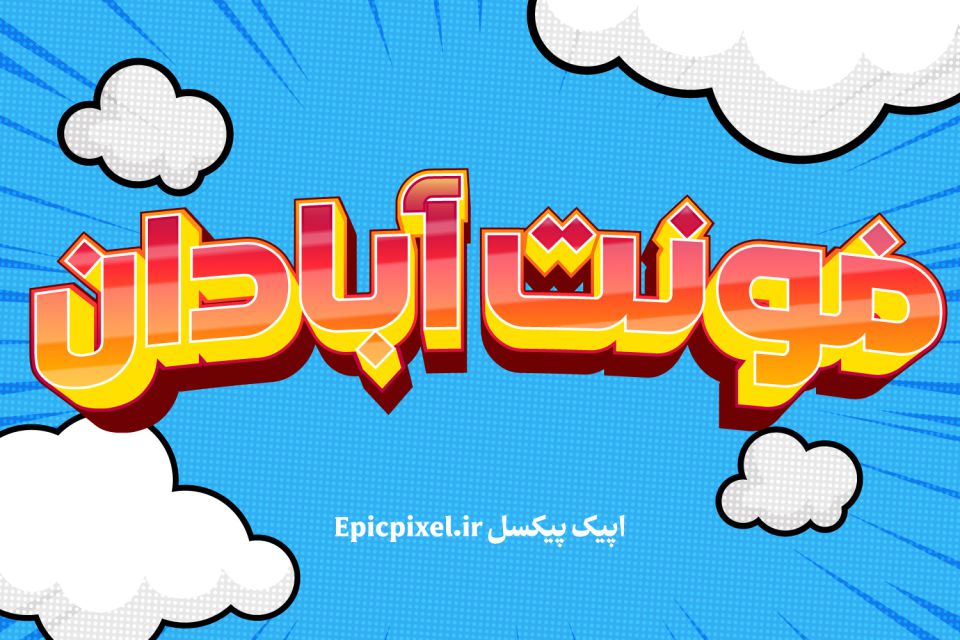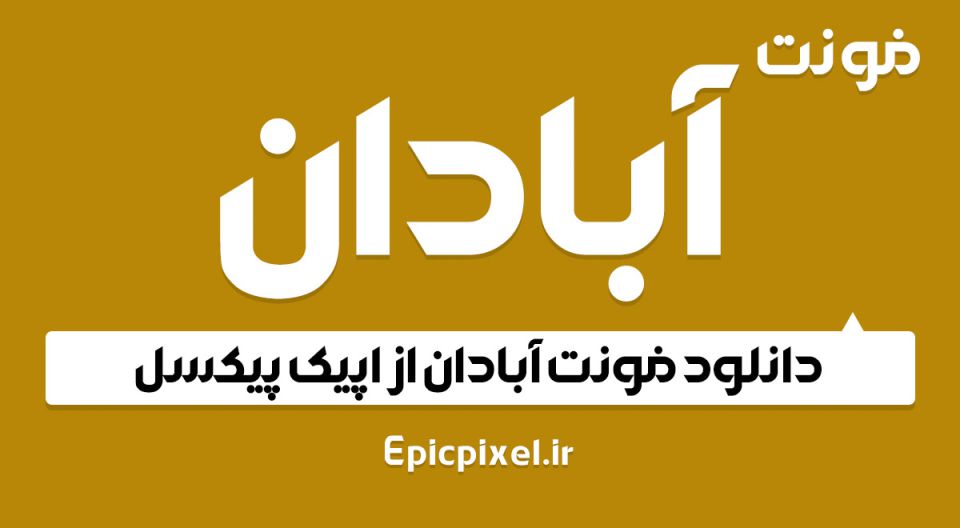
4 فونت آبادان فارسی
دانلود مجموعه کامل فونت Abadan فارسی Font اپیک آبادان |
| ⭐ توضیحات | دانلود فونت آبادان با ظاهری قدرتمند و خوانا، انتخابی ایدهآل برای طراحان گرافیک و علاقهمندان به تایپوگرافی است. این فونت برای طراحی لوگو، پوستر، وبسایت و… مناسب است.
دانلود فونت آبادان ارتقاء پروژههای گرافیکی با ظاهری قدرتمند
فونت آبادان، یک انتخاب برجسته برای طراحان گرافیک و علاقهمندان به تایپوگرافی است. این فونت با الهام از استحکام و پایداری شهر آبادان، ظاهری خوانا، حرفهای و در عین حال مدرن را به ارمغان میآورد. در این مقاله جامع، به بررسی کامل دانلود فونت آبادان، ویژگیهای برجسته آن، کاربردهای متنوع و نحوهی نصب آن میپردازیم.
چرا فونت آبادان را انتخاب کنیم؟
- خوانایی و وضوح بالا: فونت آبادان با طراحی دقیق و فاصلهگذاری مناسب بین حروف، خوانایی فوقالعادهای را برای متون کوتاه و بلند به ارمغان میآورد. این ویژگی باعث میشود تا مخاطب بهراحتی بتواند با محتوای شما ارتباط برقرار کند.
- قابل انطباق با انواع طرحها: سبک منحصربهفرد فونت آبادان، آن را به گزینهای ایدهآل برای طیف وسیعی از پروژههای گرافیکی تبدیل میکند. از طراحی لوگو و پوستر گرفته تا بروشور و وبسایت، این فونت میتواند ظاهری حرفهای و چشمگیر به کار شما ببخشد.
- ایجاد حس قدرت و استحکام: همانطور که از نامش پیداست، فونت آبادان با الهام از روحیهی پایداری و استقامت مردم آبادان طراحی شده است. این ویژگی باعث میشود تا این فونت برای طرحهایی با مضامین مرتبط با قدرت، استحکام، اعتماد و امنیت گزینهای فوقالعاده باشد.
دانلودکاربردهای متنوع فونت آبادان
- طراحی لوگو و برندینگ: با توجه به ویژگیهای ذکر شده، فونت آبادان برای طراحی لوگو و هویت بصری برندهایی که قصد القای حس قدرت، استحکام و اعتماد را دارند، بسیار مناسب است.
- عناوین و تیترهای قدرتمند: این فونت برای ایجاد تیترها و عناوین برجسته و خوانا در وبسایتها، پوسترها، بروشورها و سایر رسانههای چاپی ایدهآل است.
- طراحی بستهبندی: فونت آبادان میتواند جلوهای حرفهای و باکیفیت به بستهبندی محصولات مرتبط با صنایع مختلف از جمله لوازم ورزشی و ابزارآلات صنعتی ببخشد.
- پوسترهای تبلیغاتی: با استفاده از این فونت در پوسترهای تبلیغاتی، میتوانید پیام خود را بهصورت واضح و تاثیرگذار به مخاطبان منتقل کنید.
علاوه بر موارد ذکر شده، فونت آبادان در طراحیهای مرتبط با حوزههای زیر نیز کاربرد دارد:
- وبسایتهای خبری و تحلیلی
- پروژههای مرتبط با دفاع مقدس و ایثار
- تبلیغات محصولات و خدمات صنعتی و مهندسی
- طراحی تابلوی سردرب و تابلوهای راهنما
3. فونت آبادان چه کیفیتی دارد؟
فونت آبادان با طراحی دقیق و ظریف، از کیفیت بسیار بالایی برخوردار است. وضوح و خوانایی بالا، تنوع وزنهها و فرمتهای مختلف، این فونت را به انتخابی ایدهآل برای طراحان گرافیک و علاقهمندان به تایپوگرافی تبدیل کرده است.
5. آیا فونت آبادان جایگزینی دارد؟
فونتهای مشابهی مانند فونت میترا، فونت ترافیک، و فونت شبنم میتوانند تا حدی جایگزین فونت آبادان باشند. با این وجود، فونت آبادان با ویژگیهای منحصر بهفرد خود، ظاهری خاص و متمایز به پروژههای شما میبخشد.